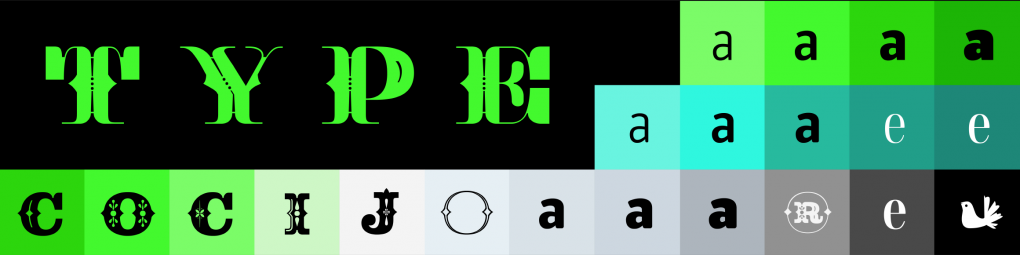
멕시코에서 왔어요. 개성 강한 라틴 브랜드사 코시호타입(Cocijotype)!
Elí Castellanos님 반갑습니다! 코시호타입에 대한 간단한 소개 부탁드려요.
저는 폰트 디자이너이자 폰트 개발자인 Elí Castellanos 입니다. 코시호타입(Cocijotype)을 나타내는 키워드로는 ‘멕시코’, ‘전통’, ‘풍미(Flavour)’ 를 꼽을 수 있어요. 코시호타입의 디자인에는 멕시코 문화의 영향이 강하게 드러나기 때문입니다. 예를 들어, 「Calavera」 폰트 디자인은 멕시코 전통 기념일인 ‘망자(亡者)의 날’이 떠오르는 매우 인상적인 폰트죠.
좋은 폰트란 무엇일까요? 또, 폰트 디자이너가 되려면 필요한 역량이 있을까요?
폰트에서 가장 중요한 것은 비율이라 생각해요. 좋은 비율은 전반적으로 폰트가 좋아 보이게 해주죠. 또한 좋은 모양은 글자 구성을 정리해 주고, 마지막으로 좋은 디테일은 세련된 느낌을 더해줍니다. 모든 것이 충족된다면 가장 좋죠.(웃음) 따라서 폰트 디자이너는 집착, 호기심, 끈기, 방법론, 계획 같은 다양한 특징들의 조합이 필요한 것 같아요.
코시호타입을 대표할 수 있는 폰트를 하나 뽑는다면요?
음. 어려운 질문이네요! 하나를 뽑아야 한다면 「Barrilito」를 선택할게요. 멕시코 문화의 일부를 장난스러운 방식으로 담아낸 폰트거든요.
문화를 장난스럽게 담았다는 표현이 멋져요. 이 폰트는 어떻게 사용하면 좋을까요?
기능적인 면에서 대문자와 작은 대문자(small cap)만 있고 소문자는 없다는 특징뿐 아니라, 재미있는 리가처(ligature)를 포함하기에 타이틀이나 서브타이틀 용도로 재미있게 사용할 수도 있죠. 제목이나 짧은 문장에 사용하거나, 시각적인 질감을 연출하는 것을 추천합니다. 짧은 텍스트로 활용하면 견고한 느낌이 들고, 긴 텍스트를 설정하면 좋은 텍스쳐를 줄 수 있답니다.